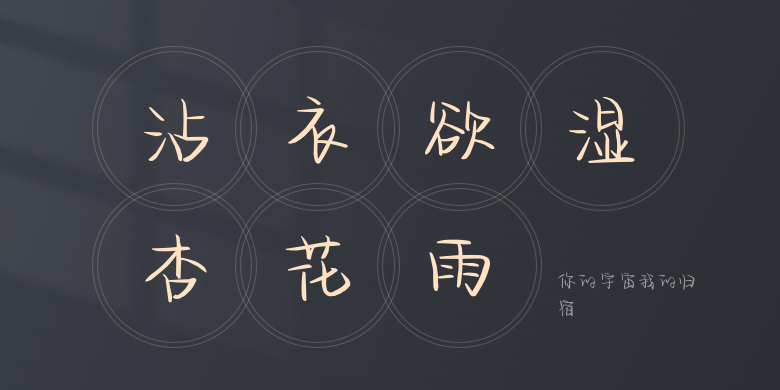
你的宇宙我的归宿
你的宇宙我的归宿,这款字体结构工整、笔画清晰,兼顾美观与易读性,适用于标题、正文、海报、包装、LOGO 等多种场景。字形优雅稳定,风格百搭耐看,适配日常排版与创意设计,让文字呈现更舒适、更具质感。你的宇宙我的归宿一笔一画,皆是细节,以均衡的比例、流畅的线条打造舒适视觉体验,字形端正大气,风格简约现代。无论是商业设计、品牌宣传还是日常排版,都能轻松驾驭,让文字更有格调与力量。你的宇宙我的归宿字体下载。